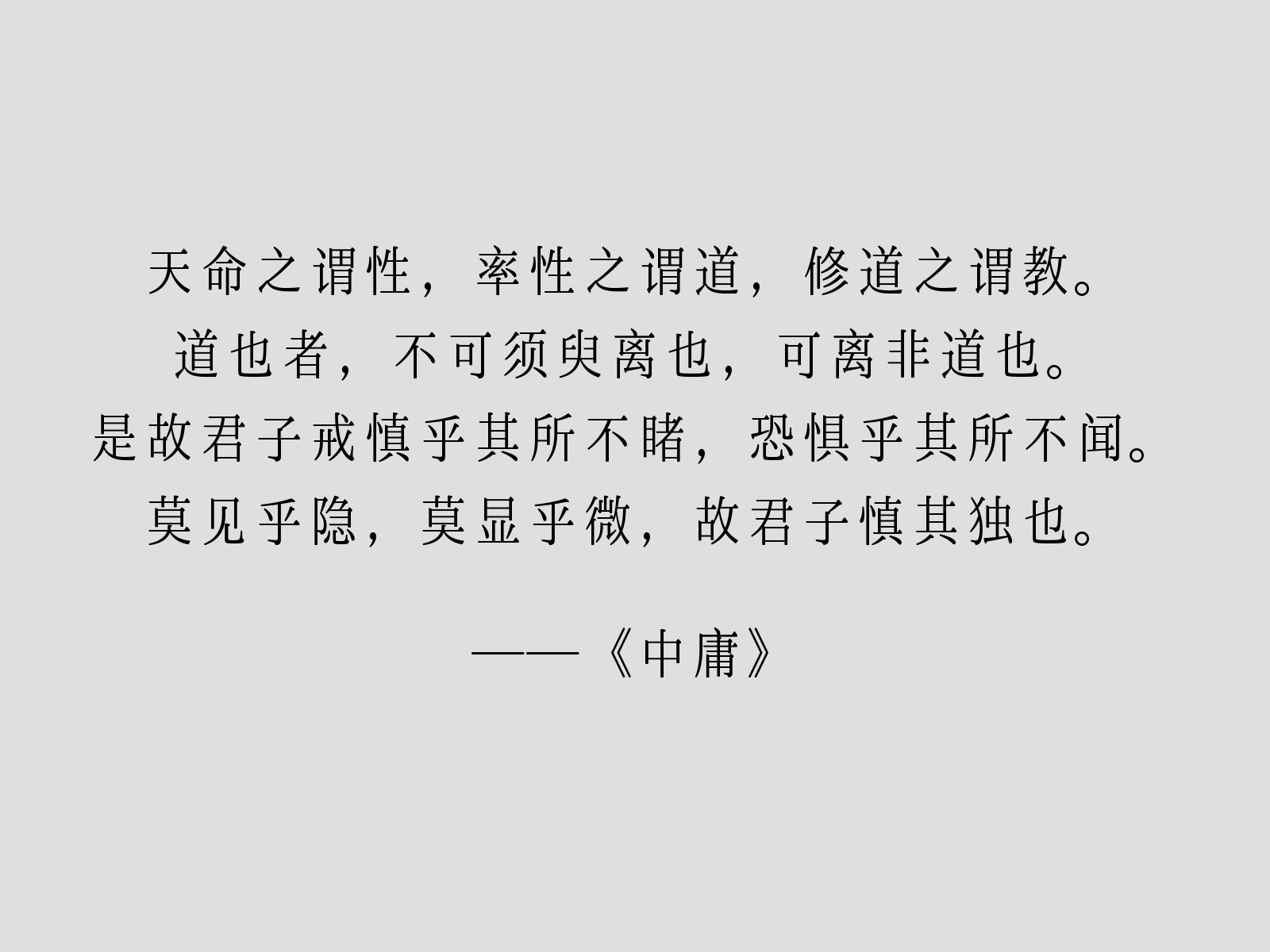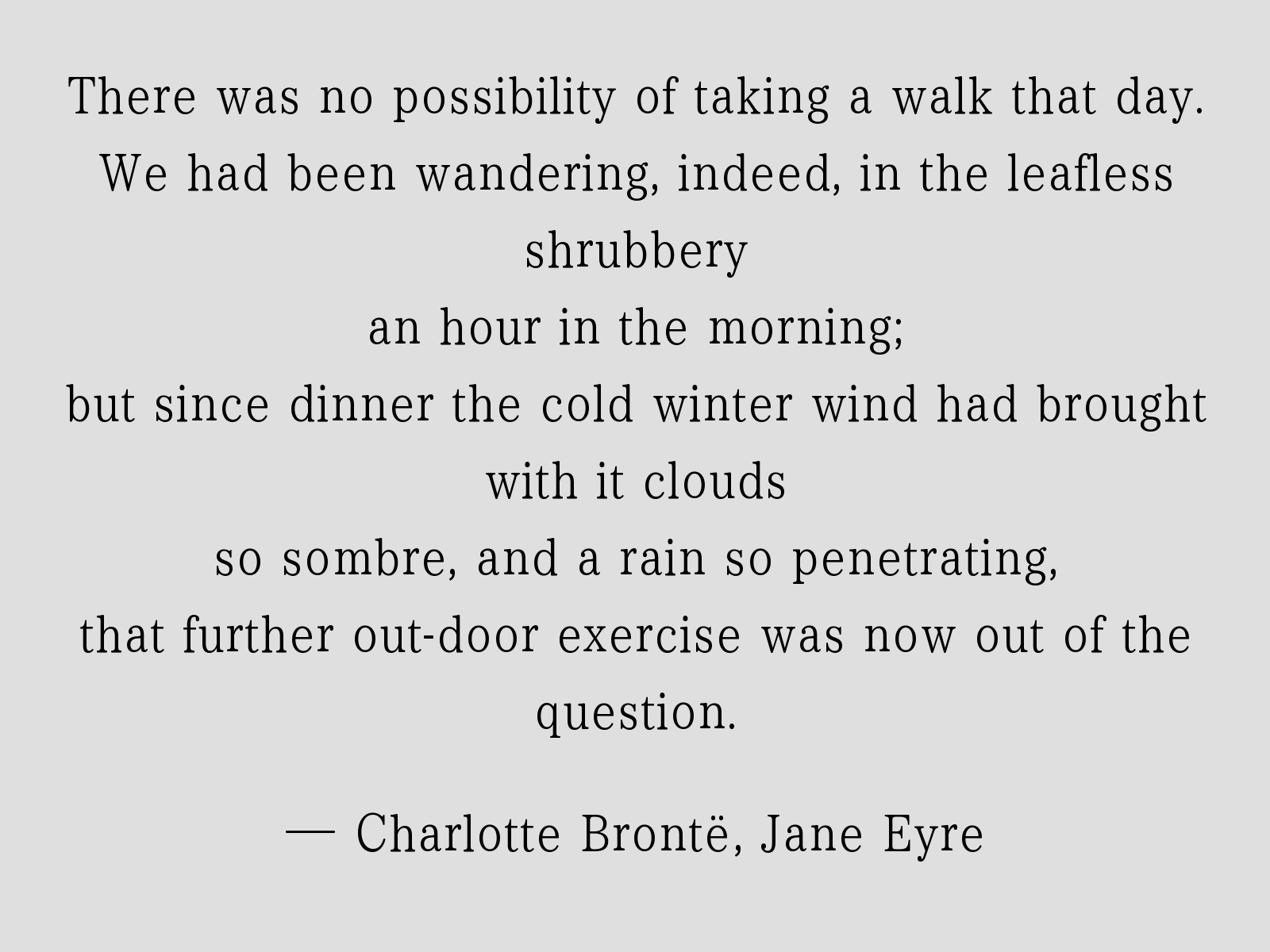
基于《霞鹜铭心宋》《霞鹜新致宋+》《致一宋体》及其原始字体的商用免费中文宋体。
将《霞鹜新致宋+》和《致一宋体》字面横向压缩 85%,并增加圆角,更加圆润、轻盈。
本字体包含简繁两版,简体版“空心晴宋体(Sky Heart Clear Serif SC)”优先采取《霞鹜新致宋+》字形,繁体版“空心晴明體(Sky Heart Clear Serif TC)”优先采取《致一宋体》字形。